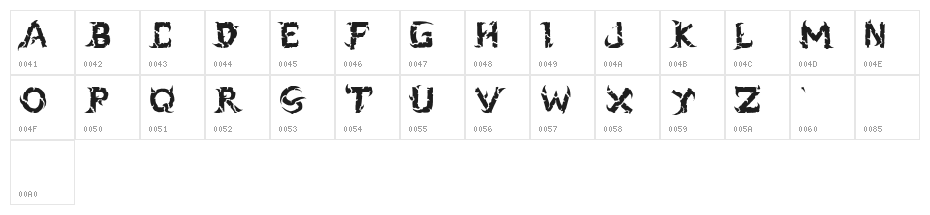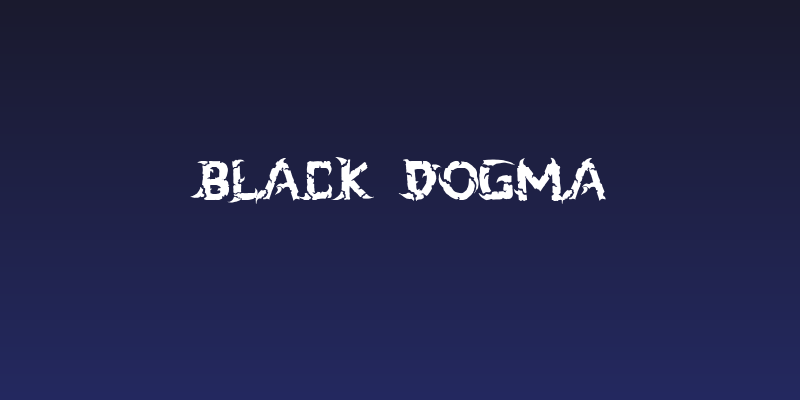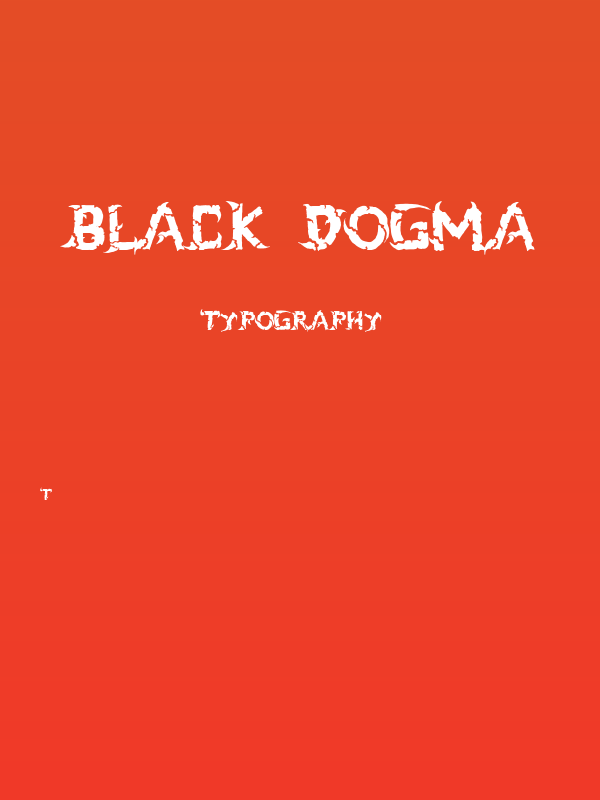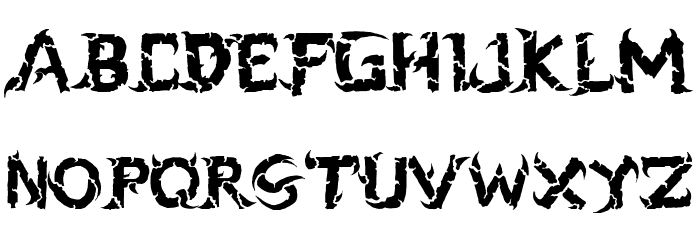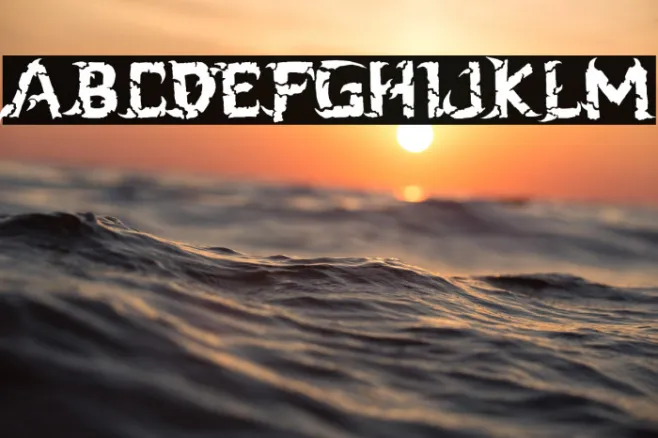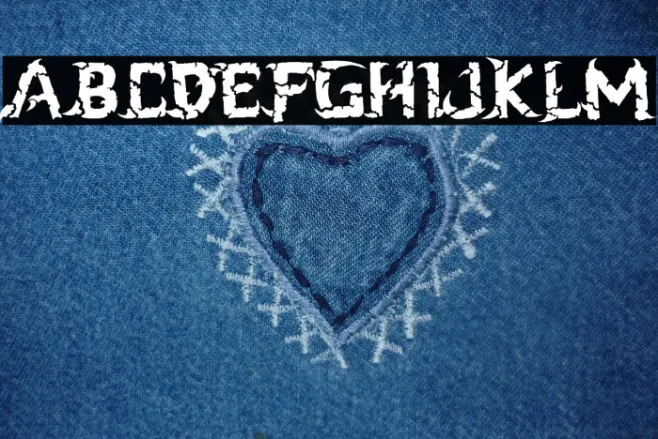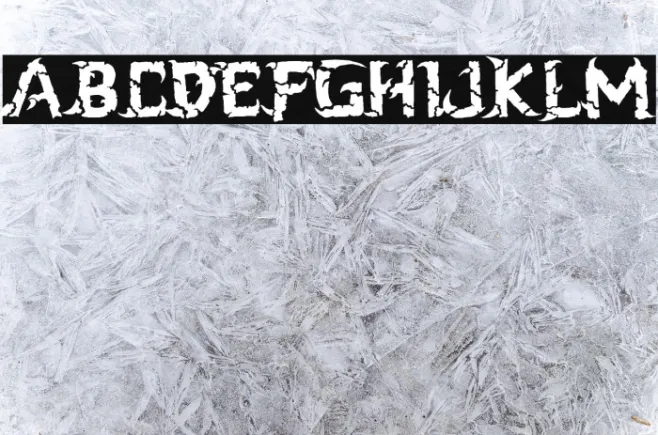
black dogma Font
✎ Distorted Eroded
| Kategorien | Distorted Eroded |
| Gesamtstil | Edgy, Rugged, Distressed |
| Anwendungsfall | Logos, Posters, Album Covers |
| Vorgeschlagene Projekte | Ideal for projects that require a bold, edgy look, such as music album covers, posters for rock concerts, or branding for extreme sports. |